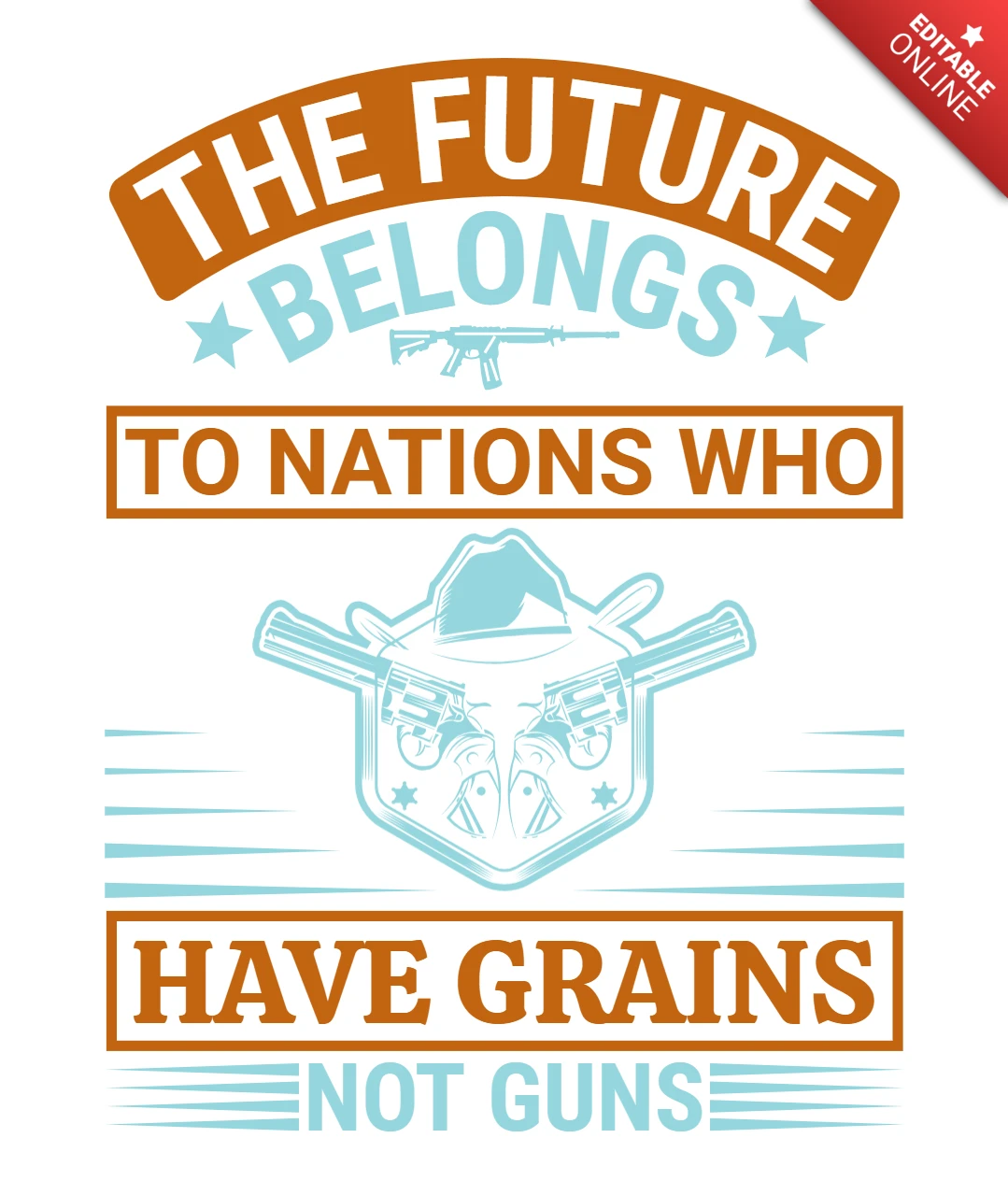
Vintage typografie ontwerpsjabloon: de toekomst is aan de naties
Bewerken in Design Studio Downloaden in JPGLaat je creativiteit de vrije loop met onze ontwerpsjabloon voor gewaagde kleding, met vintage typografie en humoristische citaten die een rebels statement maken - want de toekomst is aan naties die durven op te vallen!